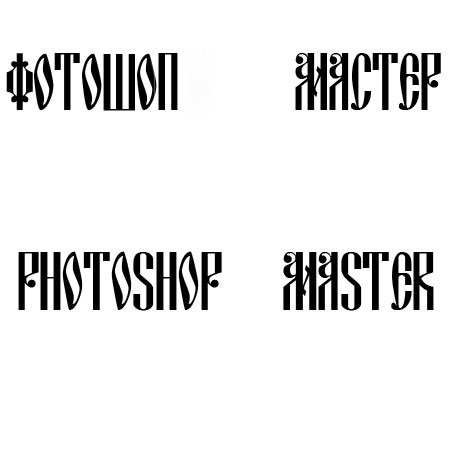
Буквы К и Ы не печатаются(((
Спасибо огромное! Это наверное самый приближенный к славянскому шрифт! Спасибо!
Красивый шрифт. Спасибо большое из Харькова.
Интересно! Это у меня одного буква Ы в фотошопе не печатается?
Отличный шрифт !!! Большое спасибо ! Скоро Пасха и шрифт очень кстати !!!